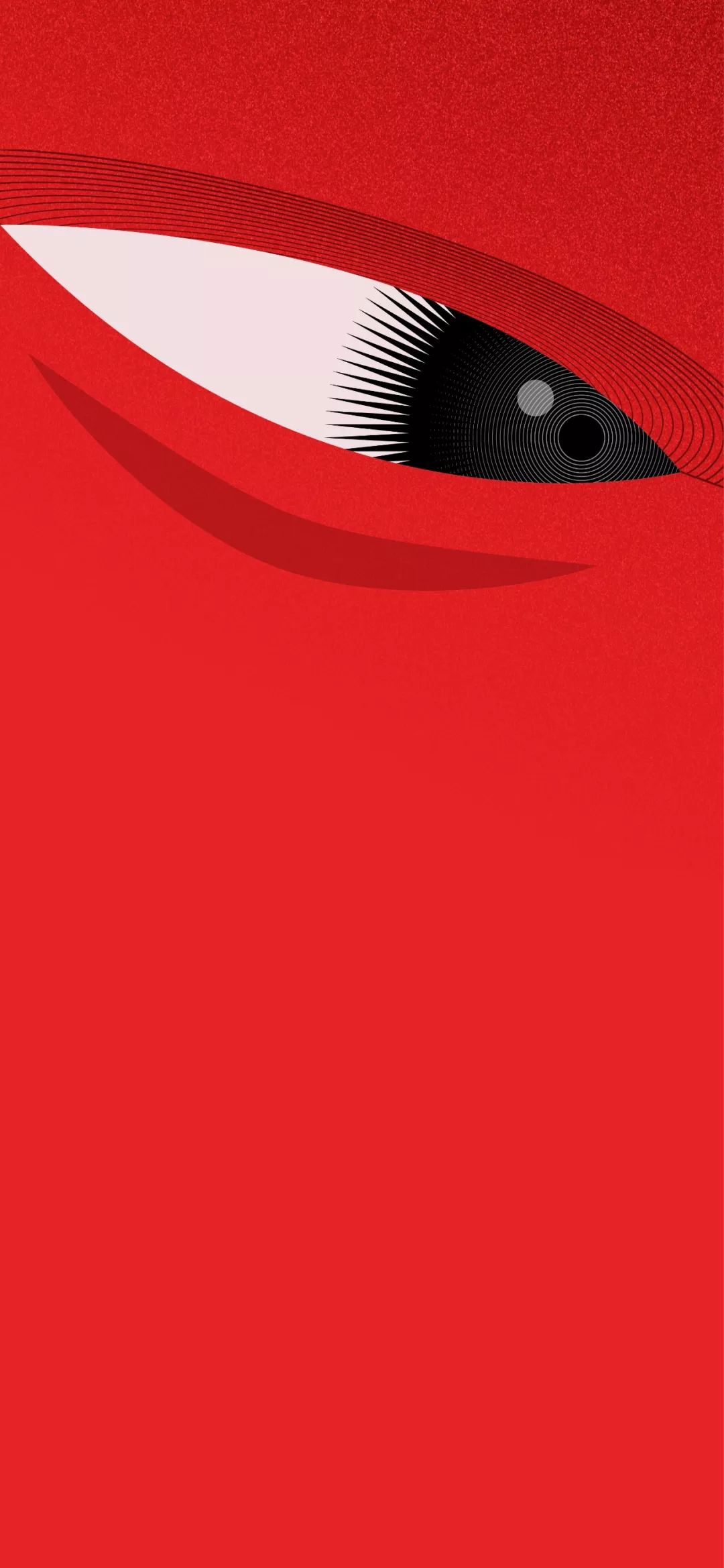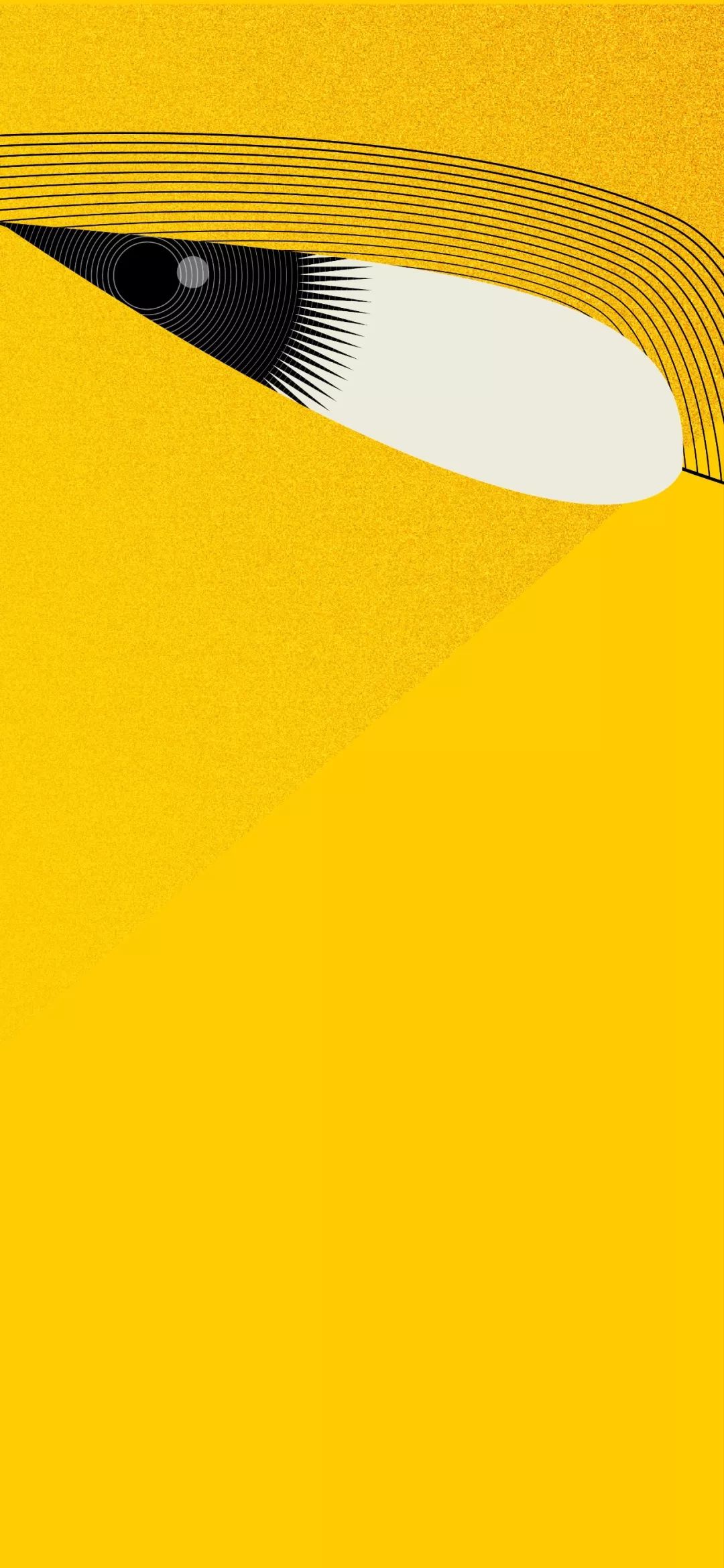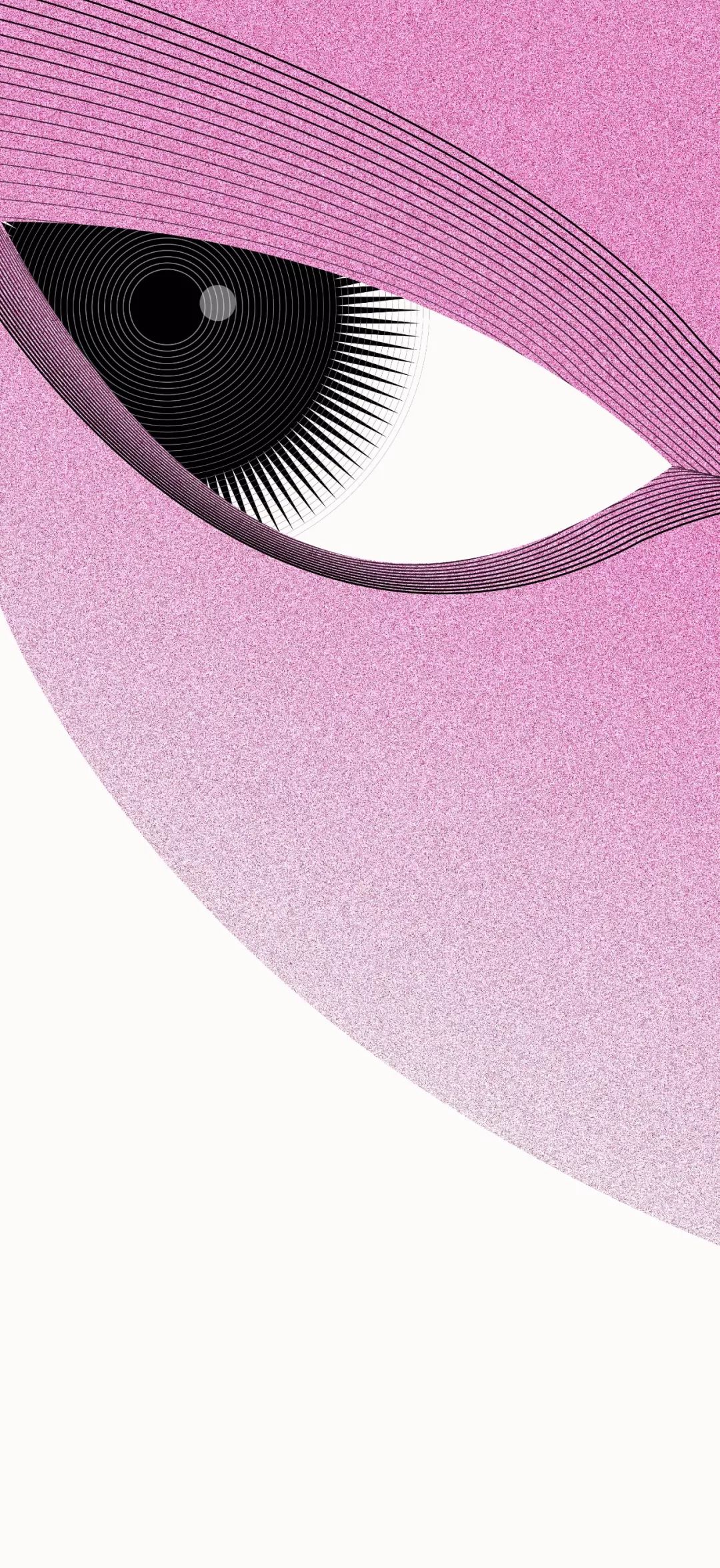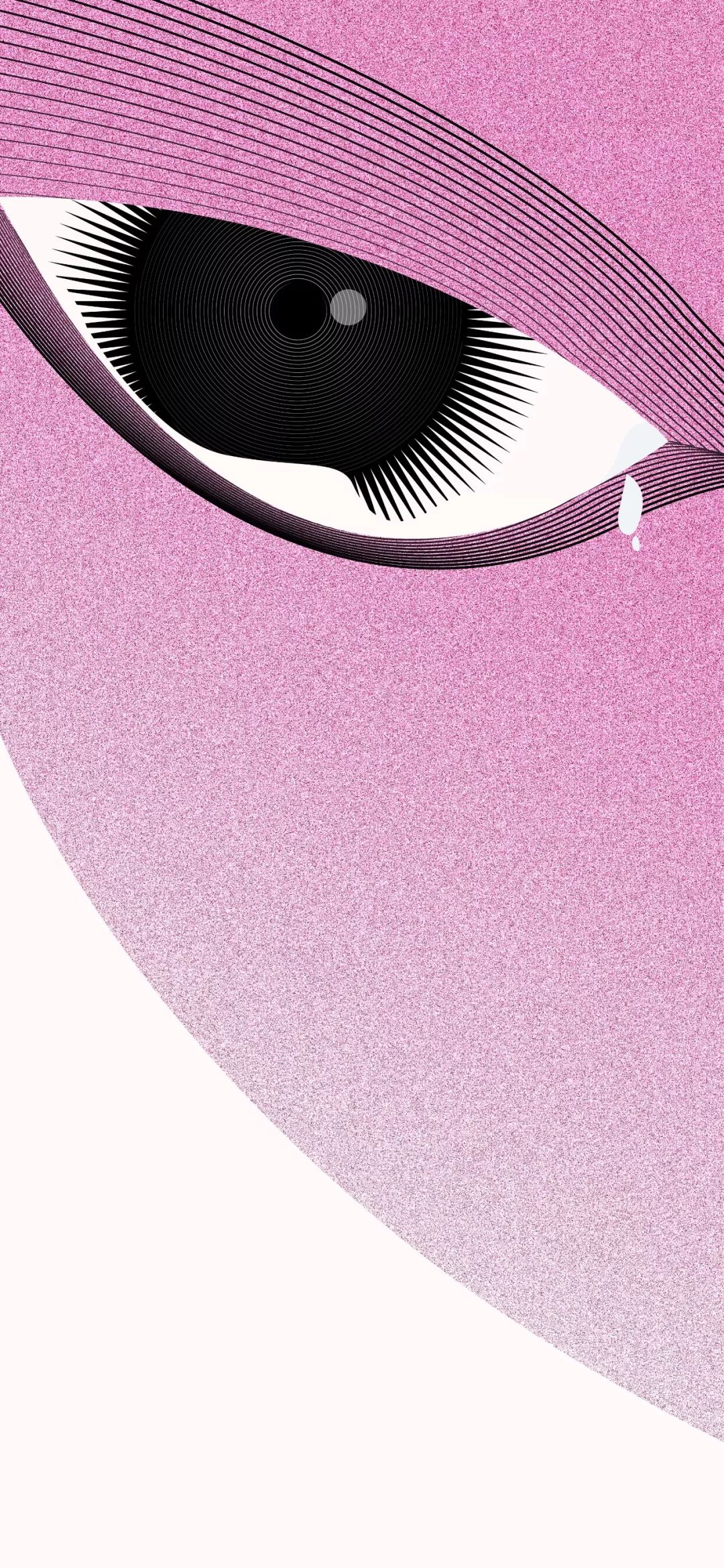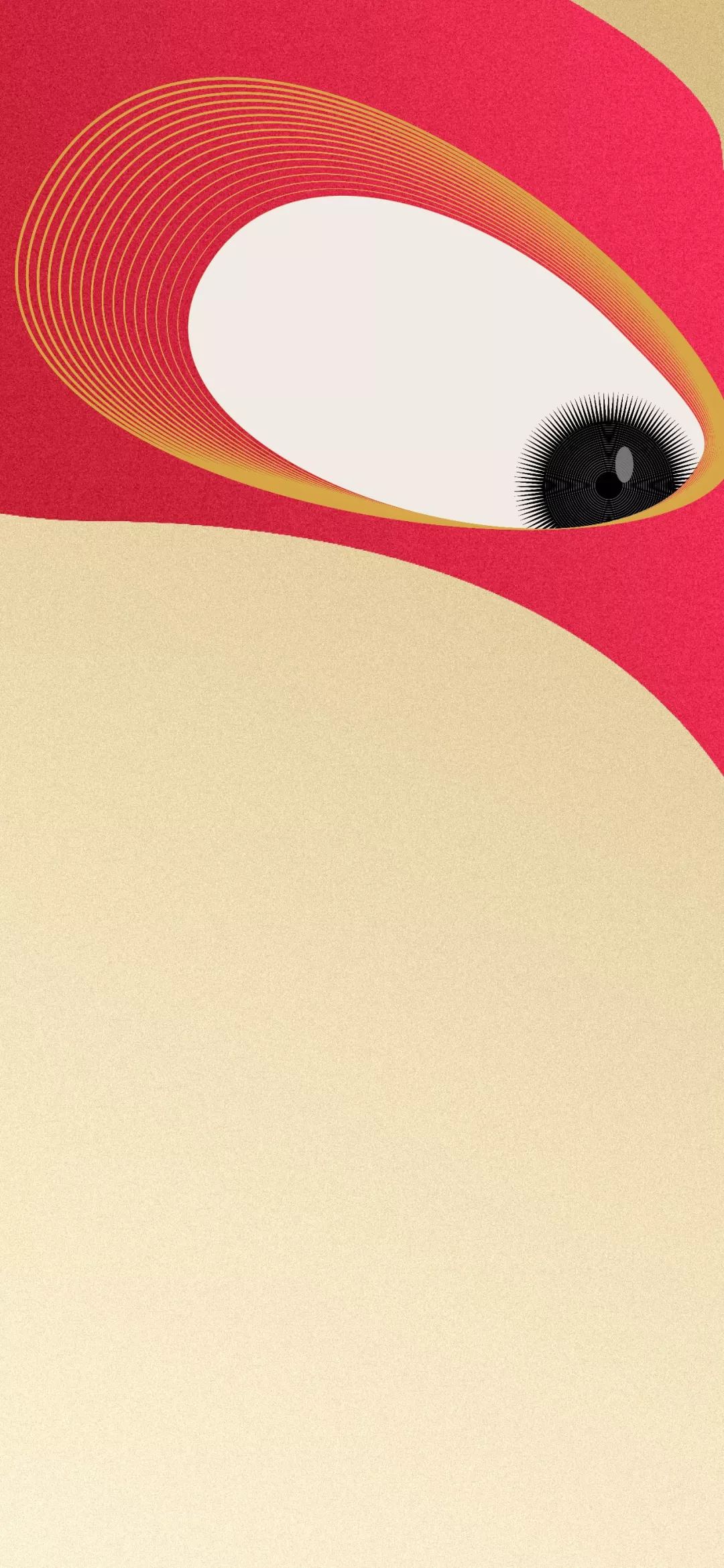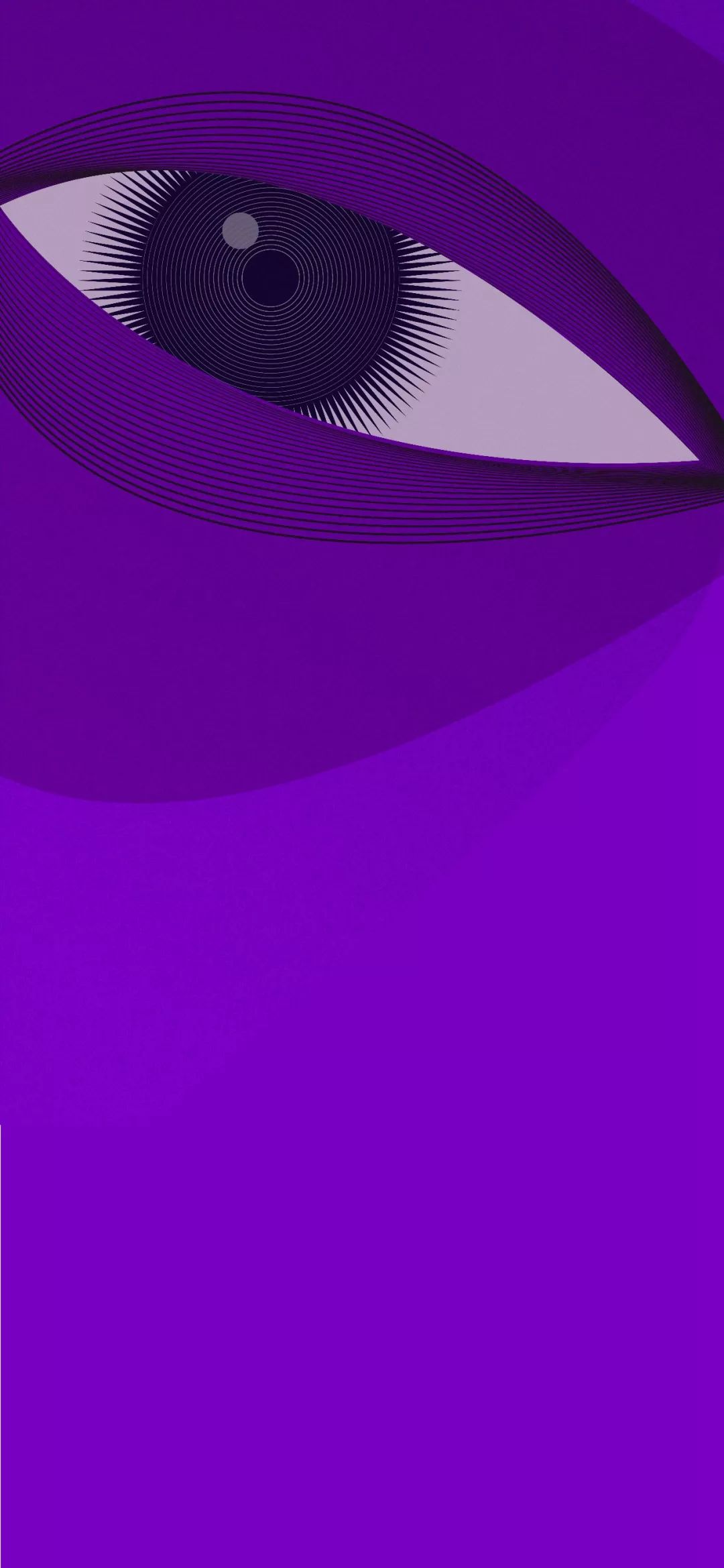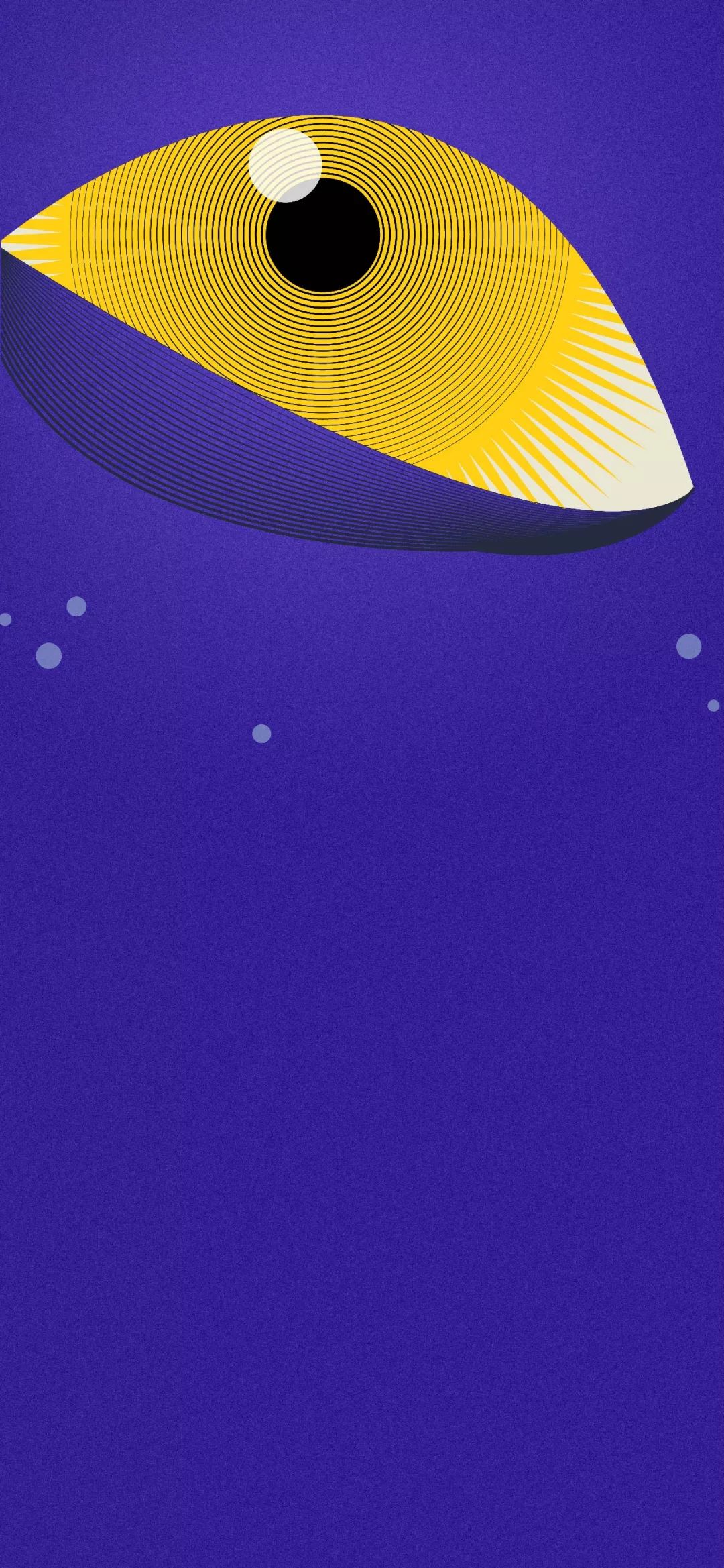
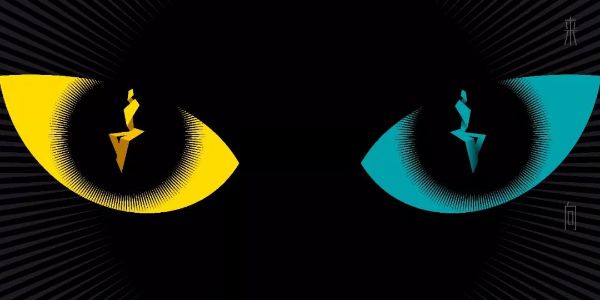
“不务正业”的潘虎,又设计了金众电影青年
猫眼娱乐×华扬联众×潘虎
金众电影青年
致敬经典,向新而生
我们突破了传统的静态形式
以兼具声、色、图、文的视频海报
带给观众视觉、听觉双重体验
▲金众电影青年官方宣传视频
金众电影青年日由猫眼娱乐、华扬联众主办,在国内首次通过票房大数据和专业评委团意见两个维度,评选年度优秀华语电影作品和电影人,致力于促进市场与专业的双向进步,凸显中国情怀和文化自信。
人为什么要看电影?
瑞典电影巨匠英格玛.伯格曼说
我的电影不是让你灵魂感到安逸
而是让你和你的灵魂战斗
金众电影青年视觉设计师潘虎认为
在现实世界与理想世界之间
电影是一次短暂的逃离
川剧变脸,“假面”下的狂欢
视频采用川剧变脸的艺术形态
将中国古典戏曲元素
与当代及西方影像艺术相结合
以此致敬经典
定义好电影应有的专业水准
并从不同情绪的眼睛中
隐喻众生喜怒哀乐
以经典致敬经典
关于“好电影”,每个人都有自己的定义。
而今我们所认同的好电影,不是一次性消费的“文化快餐”,也不是奉行娱乐至上的流行市场大量复制的“银幕暴政”。
▲视频海报GIF版
我们以八种不同色彩的脸谱分别代表八部经典电影中的角色,它们是:
红色脸谱——《闪灵》杰克·尼克尔森
表现的是恐怖、阴鸷的情绪
库布里克是潘虎最喜爱的导演之一,他擅长以冷酷严肃的纯视觉、听觉语言探讨黑暗的人性,更善于以颠覆性思维制造悲凉的恐慌。
他的高明之处在于,每个人看完电影,都能从中看到不一样的东西,得出不一样的解释。
黄色脸谱——《精武门》陈真
代表刚猛、正义、爱憎分明
粉色脸谱——《霸王别姬》程蝶衣
演绎程蝶衣的痴恋、悲情、执着
《霸王别姬》是潘虎最喜爱的一部华语电影,才华横溢的陈凯歌遇上正风华绝代的张国荣、巩俐、蒋雯丽,为我们讲述了一段凄美的传奇。
脸谱上的流泪动效,意在还原程蝶衣浓墨重彩之下的悲情绝恋。
紫色脸谱——《波西米亚狂想曲》费雷迪·墨丘利
表达对皇后乐队主唱墨丘利的敬仰与怀念
赤、金色脸谱——《大闹天宫》孙悟空
表现孙悟空的乐观与机智
绿色脸谱——《绿巨人》浩克
外眼角下垂表现内心的愤怒与暴力
蓝色脸谱——《阿凡达》涅提妮
代表忠诚、正义、勇于反抗
眼睛下的白色圆点是对角色的还原
金色脸谱——《大佛普拉斯》大佛像
表现的是佛的光明与慈悲
大佛巨眼微睁,二分观世间八分观自在
纵然心怀慈悲,却亦有难渡之人
好电影是专业审美
和大众消费的双向选择
黑色是电影的底色。电影从黑暗中开始又在黑暗中落幕,最终以真理承担社会教化的意义,而真理本身正是从黑暗晦涩中找到光明所在。
美感审判,眼睛最有发言权。观众通过这扇窗感受电影的艺术人文之美,演员通过这扇窗演绎角色的内在情绪,电影制作者通过这扇窗折射社会现实、表达人生理想。
▲金众电影青年主海报
两只眼睛代表该项目的创立者——猫眼娱乐&华扬联众,同时也代表了本次电影节评审的两大标准,即票房数据与专业审美。
眼周的散射状线条代表当代新锐导演是华语电影未来的希望之光,呼应该项目的创立背景——扶持华语新锐导演,未来,向新而生。
电影首先是消费品
消费的主体是人
卖电影就是卖座
以人喻座,观者之众代表电影的高度
电影票=电影投票
化座为人,落座之处决定人生的视角
▲金众电影青年logo
位置决定视角
一个人身处的高度不同,所看到的世界也是不一样的。对于一部电影来说,观众是旁观者、消费者,把自己代入角色去看电影,不同的角度都会有不同的理解和感受;
导演、制片人、演员是创作者,只有以观众甚至是角色的视角去做电影,才能看到什么样的电影可以触动观众。
做人也一样,身处高位,懂得俯视,才能明白成功来之不易,知道自己的责任;身处低位,仰望星空,才能看到海阔天空,明白自己的差距和不足。
人发明了电影,电影净化了社会,社会塑造了人。
布列松说,“在X眼里,电影是一种工业;Y眼中是拓阔、放大了的舞台剧;Z看到的是票房数字。”
▲金众电影青年奖杯
三人成众,金众的“众”既解构了电影与人和社会的多重关系,同时将观众、演员、电影制作者相关联,电影消费的主体也是社会的主体——人。
▲金众电影青年奖章